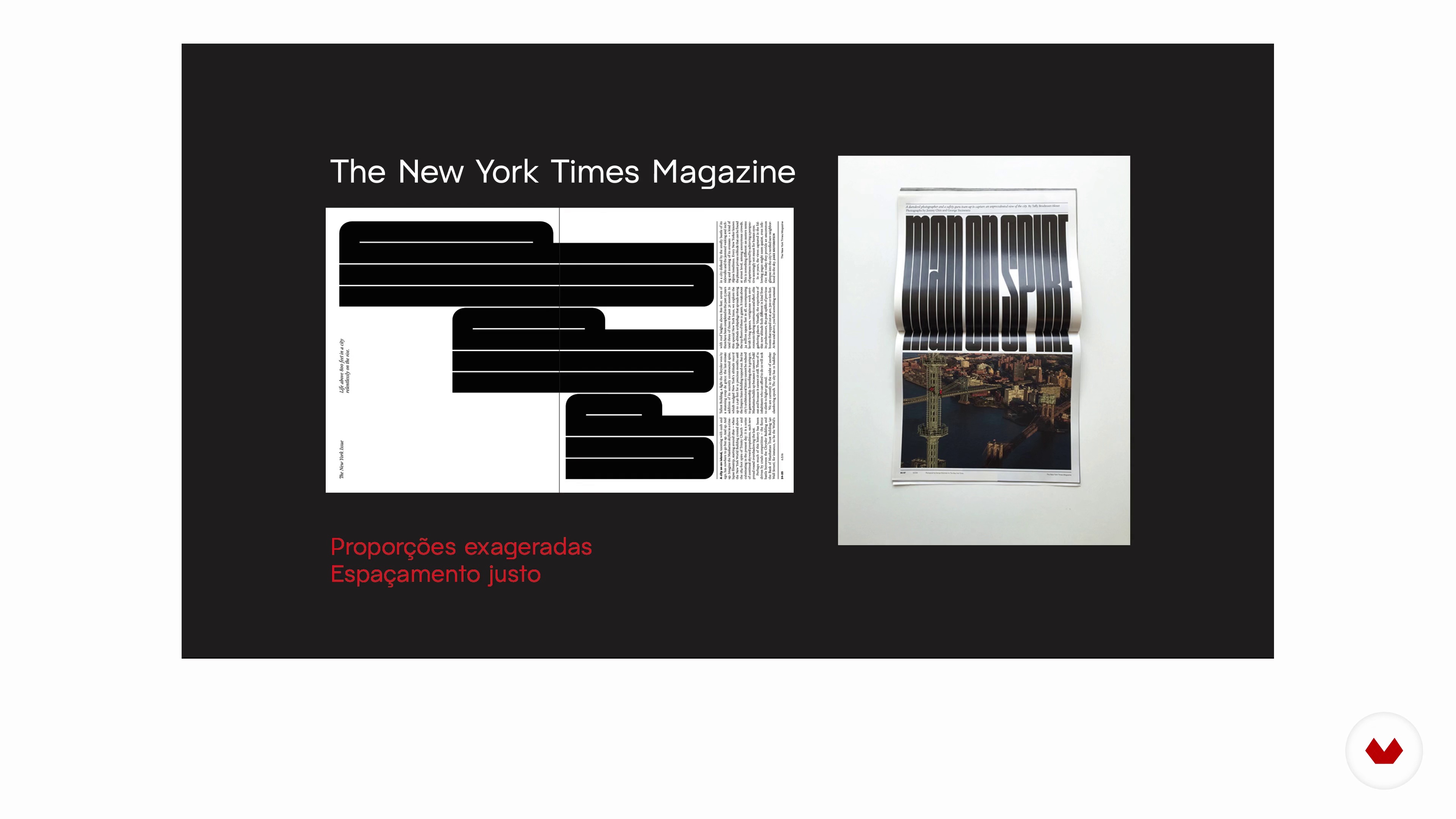
Forme et fonction
À propos de la leçon : Forme et fonction
“Vous pouvez identifier ce qu'est une source simplement en regardant les détails. Je vais vous apprendre à choisir la bonne police pour chaque application et à contourner ces règles pour créer des pièces percutantes. ”
Dans cette leçon, Álvaro Franca aborde le sujet : Forme et fonction, qui fait partie du cours Domestika en ligne : Fondements de la typographie de A à Z. Découvrez les possibilités du choix typographique pour transmettre et renforcer votre message.
“Forme et fonction Différentes sources servent des choses différentes, mais quel est le meilleur pour chaque fonction, y a-t-il une recette de gâteau? Nous apprendrons à nous identifier à partir du formulaire de lettre lui-même Qu'est ce qu'elle peut faire. Plus que suivre une recette, nous apprendrons que nous pouvons subvertir les fonctions classiques pour obtenir des messages plus puissants, allez. FORME ET FONCTION Quand on regarde la forme d'une fontaine, il y a plusieurs aspects qui nous donnent des conseils sur les fonctions qu'il peut fonctionner avec plus ou moins de succès. Je vais...”